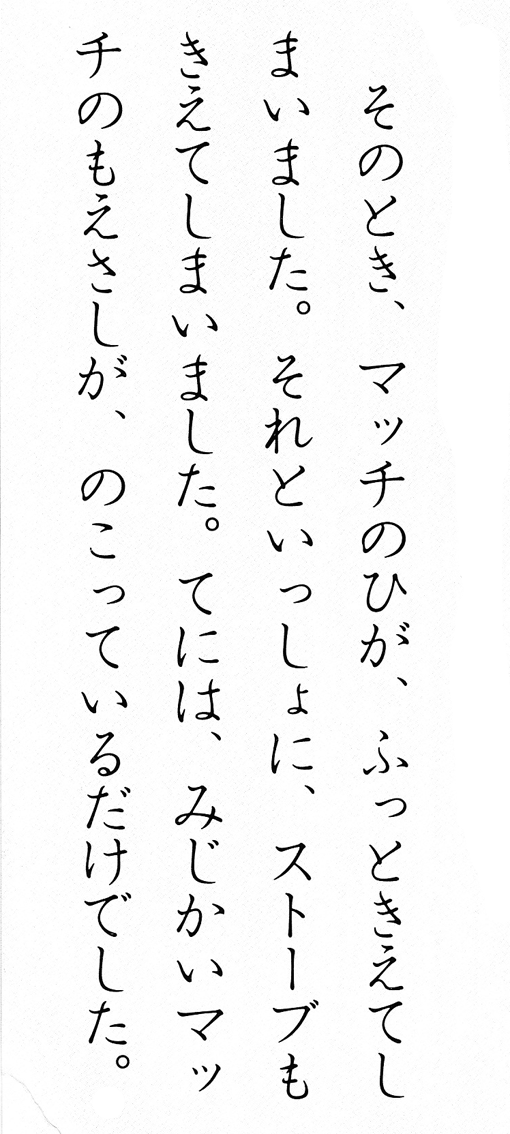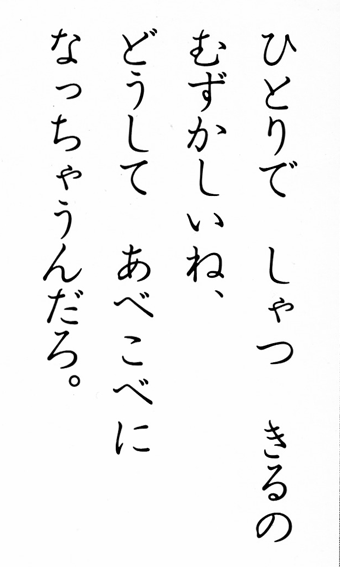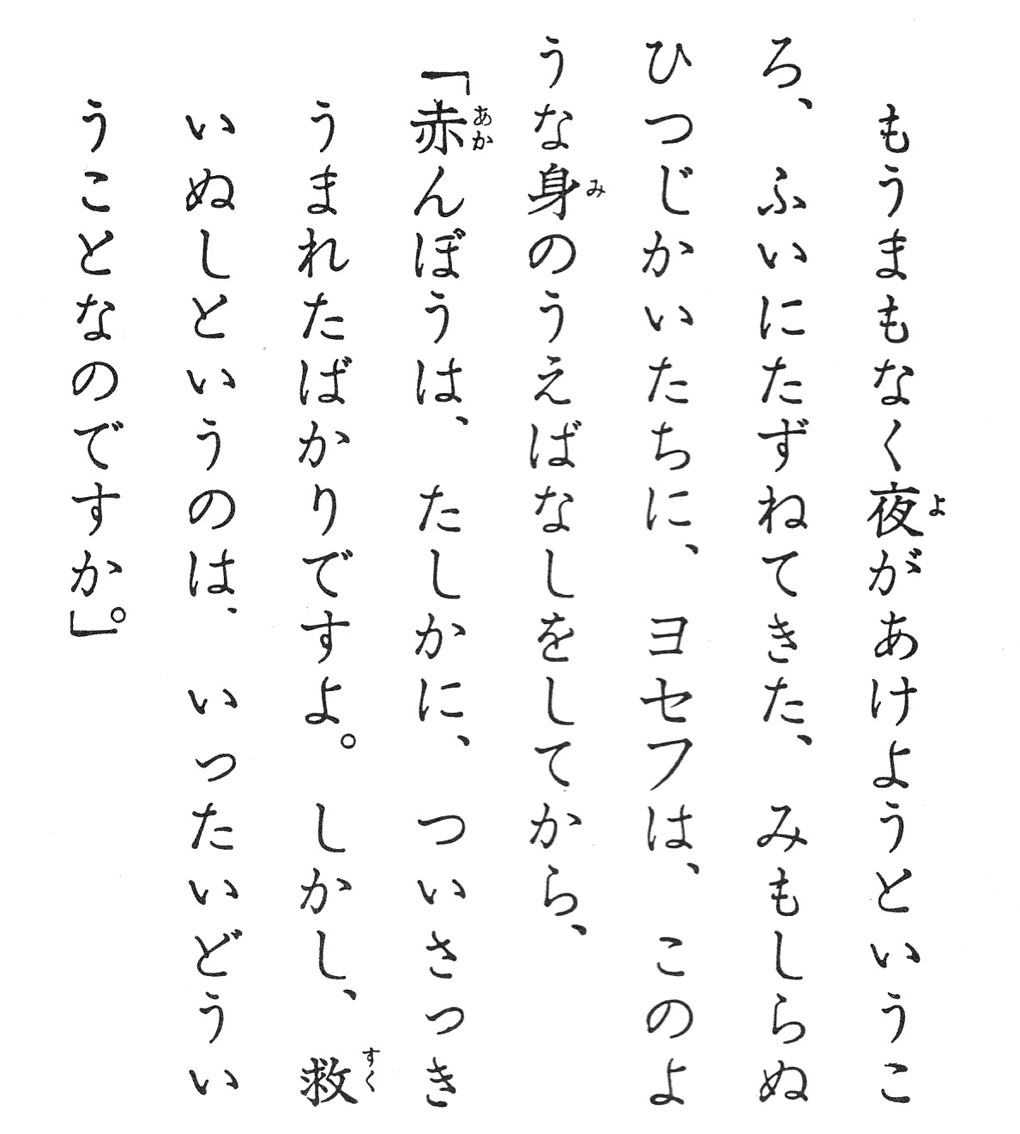
岩田母型教科書体用かな[岩教31]
九十年代の半ばまで、コンビニのおにぎりの形は、三角形しかなかったと記憶している。
フィルム包装された乾燥海苔のシートを端の切れ目からひっぱって抜きとるようになっているのだが、今みたいにきれいに外れなくて、半分以上フィルムの中に残ってしまったり、そもそも開封方法の規格が統一されていないために、どうやって中身を取りだすのか知能を試されているように感じることも度々だった(そして不器用な私は、たいてい猿以下の気持ちを味わうことになった)。
中学生のとき、その不満についてかなり真剣に考え(暇だったんですね)、友達とこんなおしゃべりをしたことがある。
「だいたい、どうしてこんな面倒なことするんだろうね」
「ごはんの水分が海苔にうつって、湿気るからでしょ」
「でもさあ、私、おにぎりは、やわらかい海苔だって好きだなあ。うん。お母さんが朝早く起きてつくってくれるおにぎりは、ひとつひとつラップに包んであるから、食べるころには海苔がヘナヘナになってるけど、すごくおいしいのに。そんなおにぎりがコンビニでも買えたらいいのに」
おにぎりくらい自分で作ろうという発想に至らないところがまったく情けないが、ともかく、それからびっくりすることがおきた。
なんと数日後に、いわゆる「直巻き」タイプのおにぎり(海苔がシットリしている丸型のもの)が発売されたのだ。友達と大笑いをした。
まったくどうでもいい話のわりに、そんなことを今でも覚えているのは、世の中の商品やサービスに対して、「こんなものがほしい」と自分の頭で考えたことも、それが現実になったことも、初めての経験だったからではないかと思う。
そんなことが、これまでにいったい何度あっただろう。
思いだそうとしてもなかなか出てこない。
かつて想像もしていなかった便利なものや、なくてはならないものが、今は中学生のときより遥かにたくさんあるのに。
コンビニがない時代にはもう戻れる気がしないけど、自分はせいぜい直巻きのおにぎりがあれば十分な人間だったのではないか、という考えに、時々とてもこわくなる。
誤解を恐れずに言えば、今回の書体は、どう考えてもバリッと歯切れのいい寿司屋の海苔ではない。山や海で食べるおにぎりみたいに、ちょっと湿気にあてられた海苔である。
でも私はこの書体が大好きだった。
初めての出会いは『こどものとも』だ。
子供心に、変わった文字だなあと思ったのを憶えている。そして、慣れると妙にくせになる、とも。
そのときは好きな理由がわからなかったけれど、たぶん、この書体でかかれた言葉の、ちょっとしんなりしたような温かみのせいではないかと思う。「直巻き」のおにぎりのおいしさと、この書体の心地よさは、すごく似ているような気がする。
それが〈岩田母型教科書体用かな(岩教31)〉という名前の写植書体だと知ったのはつい最近のことだ。
前身の岩田活字が存在することも、「教科書体」だったことも、今回初めて知っておどろいた。
現在の教科書体のイメージとはかなり違うけれど、子供のころしか見る機会がなかったのもそれで納得がいく。
正直なところ、モリサワの見本帳でこの書体を発見するとは思わなかった。私はこれまで、モリサワ書体は積極的にオープン化されたというイメージをもっていたのだが、中にはDTPに受け継がれなかった書体もあって、それらはむしろ写研書体よりずっと見る機会が少なくなっているのかもしれない。
ポプラ社から出ていた『子どもの伝記全集』でも、この書体がつかわれていたのを憶えている。
なぜかいちばん印象に残っている巻は『キリスト』で、当時通っていたカトリック系の幼稚園にこの本があったことも、クリスマスの劇の発表会でマリア様役(人生初の晴舞台!)を射止めたことも、だからこの本がちょっと特別だったことも憶えている。それらの記憶が全部混ざり合って、見分けがつかない。
慣れ親しんだ書体にはふしぎな原動力がある、と思うのはそういうときだ。
海が見えない場所で、潮の香りに気づいたときみたいに、景色の先を見たくなる。坂道を下るように、どんどん頁を読み進めたくなる。
ちなみに、「コンビニ直巻きおにぎりの考案者になりそこねた」出来事について、ひとつだけ白状するなら、あのとき私は「誰でも考えることだったんだね」と言って照れくさく笑いながら、本当は心の底で、「自分のおかげじゃないかな」と思ったのだ。
言葉にしたから叶ったんじゃないか、と。
その想いが根底にあるから、今でもこりずにこんなことを書いているのかもしれない。